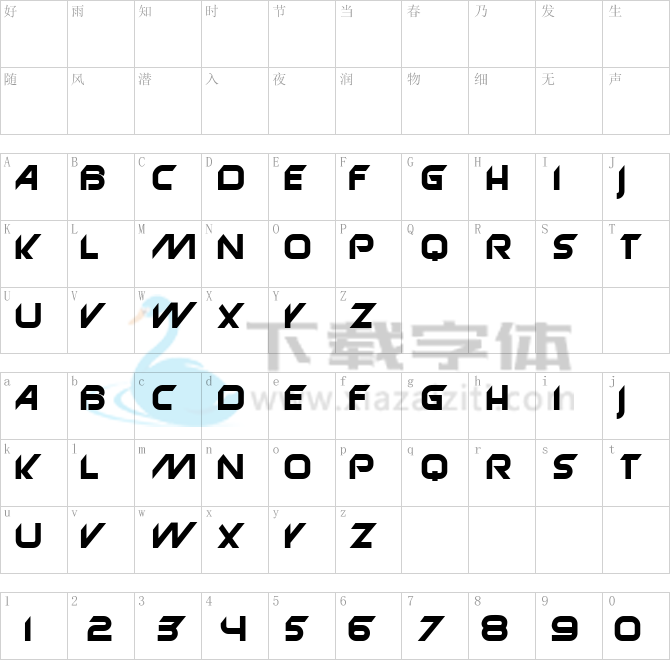
Anniversary.ttf字体下载,这款字体结构工整、笔画清晰,兼顾美观与易读性,适用于标题、正文、海报、包装、LOGO 等多种场景。字形优雅稳定,风格百搭耐看,适配日常排版与创意设计,让文字呈现更舒适、更具质感。Anniversary.ttf字体下载一笔一画,皆是细节,以均衡的比例、流畅的线条打造舒适视觉体验,字形端正大气,风格简约现代。无论是商业设计、品牌宣传还是日常排版,都能轻松驾驭,让文字更有格调与力量。Anniversary.ttf字体下载字体下载。